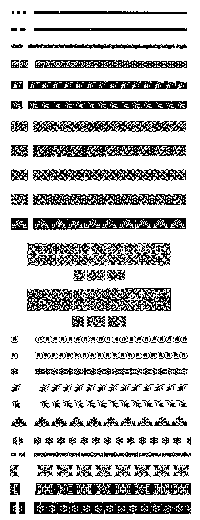
ОТДЕЛ НАБОРНЫХ ШРИФТОВ НИИПолиграфмаша и отечественное шрифтовое дело М. Г. Ровенский |
ОКОНЧАНИЕ. ПРОДОЛЖЕНИЕ В №2. НАЧАЛО В №1 Лаборатория наборных орнаментов и декоративных шрифтов Одновременно с изобретением книгопечатания появились украшения на печатных страницах. Известны образцы использования наборных орнаментов такими крупными деятелями типографского искусства, как Клод Гарамон, Иван Федоров, Эльзевиры, Уильям Моррис и многие другие. В оформлении печатных изданий применяются и абстрактные украшения—простейшие линейки, геометрические фигуры. Словолитни и типографии в царской России имели очень большое количество комплектов наборных орнаментов, зачастую низкого художественного качества. После революции большая часть их была переплавлена в металл. Таким образом были разработаны целые серии орнаментов для ручного набора. В серии «Слава» (худ. Н.Я.Караванский, А.Н.Коробкова) использованы лавровые и дубовые листья с советской эмблематикой. В серии «РСФСР» (худ. Н.Я.Караванский, А.Н.Коробкова, И.С.Слуцкер) взят исходный мотив—лиственный орнамент, названный «Федоровским», который употреблялся на протяжении столетий в старопечатных книгах. В серии «Белорусская ССР» (худ. А.Г.Платунова, А.Н.Коробкова) введены мотивы белорусской вышивки. В серии «Казахская ССР» (худ. А.Г.Платунова, А.Н.Коробкова, Е.Г.Бельская), в серии «Узбекская ССР» (худ. А.Г.Платунова, И.С.Слуцкер, А.Н.Коробкова), в серии «Киргизская ССР» (худ. И.С.Жихарев, Н.А.Перова), «Таджикская ССР» (худ. А.Г.Платунова), «Туркменская ССР» (худ. А.Г.Платунова), «Карельская АССР» (худ. А.Г.Платунова)—во всех перечисленных сериях использовались мотивы соответствующей народной орнаментики. Каждый наборный орнамент, основанный на элементах народного искусства отдельных национальных республик, обогащает художественное оформление издательской продукции, но его применение требует большого внимания и такта. К сожалению, эта большая работа ОНШ, потребовавшая много творческих усилий и материальных затрат, не была полностью использована и внедрена в оформительскую практику издательств. Поход в 60-е годы против «украшательства» в архитектуре сказался и на издательской практике: все это было признано «излишеством». Теоретические работы Основная работа Отдела новых шрифтов всегда состояла в решении художественно-конструкторских задач по проектированию рисунков шрифтов для типографского набора, однако вопросы теории шрифта и истории развития типографского дела также требовали внимания и изучения. Вопросы проектирования и анализ художественного качества шрифта. Практическая деятельность по созданию новых рисунков шрифта требует теоретического исследования, познания эволюции шрифтовых форм и закономерностей их развития. Проводились также и параметрические работы, связанные с различными видами и требованиями проектирования и эксплуатации шрифтов. На основе обобщения отечественного опыта по освоению и использованию зарубежных разработок шрифтов Ф.Ш.Тагиров написал работу на тему «Технологический процесс разработки рисунков копируемых шрифтов». В 1946 году в журнале «Полиграфическое производство» была опубликована статья Ф. Ш. Тагирова «Состояние и перспективы развития печатных шрифтов в СССР». Значительное теоретическое исследование провел Ф.Ш.Тагиров в своей статье «Язык, письменность, шрифт», опубликованной в сборнике «Проблемы рукописной и печатной книги» (М., 1976). Рассматривая вопросы взаимосвязи языка, письменности и шрифта, он пришел к выводу, что «...существует закономерная связь письменности с языком, шрифта с письменностью...» Психофизиология восприятия и удобочитаемость шрифтов Изучение законов зрительного восприятия шрифтов позволяет определить их удобочитаемость как основной показатель качества текстового шрифта. При определении удобочитаемости шрифта нужно учитывать не только легкость распознавания графем, но и пластическое решение шрифта, его художественную форму, эстетику восприятия. В 1945 году профессором В.А.Артемовым и Е.Н.Меллер был составлен обзор экспериментальных работ и исследований в области удобочитаемости шрифтов за период 1935–1945 годы. Наряду с этими исследованиями в ОНШ велись работы по определению величины допусков на межбуквенные пробелы, по установлению зависимости удобочитаемости текстового шрифта от формата полосы набора, по определению пределов использования одного базового рисунка для изготовления пуансонов нескольких кегелей и многие другие. Работы по исследованию опыта в вопросах искусства шрифта и при проектировании типографских шрифтов В 1950–1957 годах под руководством Ф.Ш.Тагирова в отделе была проведена работа по обобщению опыта ведущих мастеров книжного оформления в области искусства шрифта и исследования по вопросам проектирования типографских шрифтов, разрабатываемых художниками отдела. Г.А.Банникова в своем отчете «Процесс проектирования Банниковской гарнитуры» поделилась опытом критического использования исторического наследия при создании своей гарнитуры и прослеживает поиски основного различия между типами шрифтов, рассматривая вопросы классификации. Н.Н.Кудряшев в своем труде «Опыт проектирования текстового шрифта для набора газет» рассказал о первом опыте по разработке отечественного газетного шрифта и сформулировал основные требования, которым должны отвечать газетные шрифты. М.Г.Ровенский в своем исследовании «Шрифт в книжном оформлении Д.А.Бажанова» описал мастерство графических работ Д.А.Бажанова в книжном оформлении, его индивидуальную манеру рисунка шрифта—«Бажановский почерк» и возможность использования рисунка его шрифта для разработки типографской гарнитуры. Выпуск информационных проспектов В Отделе новых шрифтов по мере разработки новых типографских гарнитур возникла необходимость выпуска информационных материалов для ознакомления типографий и издательств с новыми шрифтами, а также для использования этих шрифтов в издательской практике. Особо выделяются по оформлению проспекты, сверстанные по макетам самих авторов—создателей типографского шрифта. Информационный проспект к гарнитуре Акцидентная Телингатера решен по макету С.Б.Телингатера. Признанный мастер искусства книги, долгие годы занимающийся графикой типографского шрифта, показал различные возможности применения своего шрифта в печатной продукции. Известный оформитель книги, мастер каллиграфического шрифта П.М.Кузанян представлен двумя проспектами: к гарнитуре Титульная Кузаняна для строкоотливного, крупнокегельного «СК» и ручного набора, а также к афишно-плакатному шрифту Гранит для ручного набора. Типографский шрифт Пискаревская гарнитура, созданный одним из крупнейших ксилографов, мастером книжной гравюры и оформления книги
Н.И.Пискаревым, показан в различных текстах книжного набора в сочетании с гравюрами и заставками работы автора. Благодаря таким людям можно было выполнять нужную работу по выпуску информационных проспектов. В связи с этим необходимо вспомнить активного участника выполнения всех этих работ по выпуску информационных проспектов А.А.Оносовского. Прошедший воинскую службу матросом, а затем работавший в типографии печатником, он обладал огромной трудоспособностью и любовью к труду. В процессе подготовки к изданию очередного проспекта он доставлял в типографии матрицы типографских гарнитур с набором и сам помогал печатнику готовить печатную форму. Последние годы своей работы в ОНШ он стал мастером-фотографом и добивался блестящих результатов в процессе подготовки оригиналов рисунков шрифта к дальнейшей разработке. Он остался в памяти всех его соратников по работе! |
Наборный орнамент из проспекта–инструкции Советский наборный типографский орнамент, (серия №6), Москва–1959 Наборный орнамент из проспекта–инструкции Советский наборный типографский орнамент, (серия «БССР»), Москва–1961 Лицевая сторона проспекта Новая журнальная гарнитура, Москва–1973 Обратная сторона проспекта Новая журнальная гарнитура, Москва–1973 Лицевая сторона проспекта Гарнитура «НЕВА», Москва–1973 Обратная сторона проспекта Гарнитура «НЕВА», Москва–1973 Лицевая сторона проспекта Гарнитура акцидентная ТЕЛИНГАТЕРА, Москва–1971 Лицевая сторона проспекта Титульная гарнитура «ЛИДИЯ», Москва–1971 Обратная сторона проспекта Титульная гарнитура «ЛИДИЯ», Москва–1969 Лицевая сторона проспекта Афишно–плакатный шрифт «ГРАНИТ», Москва–1966 Обратная сторона проспекта Афишно–плакатный шрифт «ГРАНИТ», Москва–1966 Лицевая сторона проспекта Гарнитура «НАСХИ КНИЖНЫЙ», Москва–1971 Обратная сторона проспекта Гарнитура «НАСХИ КНИЖНЫЙ», Москва–1971 |
Персоналии Теперь , рассматривая деятельность Отдела наборных шрифтов за весь обозримый более чем пятидесятилетний период (1938–1993), нужно признать, что сложившийся коллектив работников отдела сохранил традиции русского типографского шрифта и старался использовать в своей работе мировой опыт развития типографского искусства. |
Ф.Ш.Тагиров, основавший и многие годы возглавлявший отдел, прошел школу Фаворского в двадцатые годы во ВХУТЕМАСе. Обладая обширными знаниями и широким кругозором, он разрабатывал большой круг вопросов по проектированию новых типографских шрифтов и технологии их производства на всех этапах в процессе освоения. Тагирову принадлежит приоритет в создании первых в стране шрифтов особых графических форм, в частности, арабских, индийских и корейских. Он оставил ряд исследовательских работ по вопросам теории шрифта и истории развития типографского дела. Тагиров пользовался большим авторитетом среди художников, типографских и издательских работников. Недаром многие художники-графики называли ОНШ «институт Тагирова». В начале 60-х годов ему ампутировали ногу, но он продолжал работать до 1978 года. |
Н.Н.Кудряшев—первый художник отдела, взявшийся за разработку первого отечественного газетного шрифта. Он создал по разработанной им совместно с З.А.Масленниковой методике самое большое количество типографских гарнитур для различных типов изданий. Среди его шрифтов всеми признанная гарнитура Кудряшевская энциклопедическая, разработанная в 5-ти начертаниях в огромном ассортименте знаков (русских, латинских, греческих, математических, нотных, астрономических, лингвистических, готических, кириллицы, глаголицы и многих других). Ее применение в третьем издании 30-томной Большой Советской Энциклопедии принесло издательству экономию в 4 с лишним миллиона рублей. А гарнитура Словарная Кудряшева, использованная издательством «Русский язык» для набора на 124-х языках народов мира, потребовала разработки тысяч рисунков шрифтовых знаков. Кудряшев отличался необычайным профессионализмом в работе и доскональным знанием наборной техники. Он был одним из немногих проектировщиков наборного шрифта, разрабатывавшим в своих гарнитурах капительные знаки. Кудряшев обладал огромной работоспособностью и оставил после себя большое количество невостребованных замыслов и эскизов, которые могут и должны быть использованы. |
Г.А.Банникова прошла основательную школу как художник-график в ленинградской Академии художеств еще в 20-е годы. Профессор В.А.Левицкий, знаток истории искусства шрифта,который вел курс искусства шрифта в Академии художеств, способствовал тому, что Банникова в своих творческих замыслах пыталась раскрыть художественную ценность типографского шрифта. В своей гарнитуре Банниковская, над которой она работала много лет, на основе тщательного изучения первых русских шрифтов петровского времени и европейских шрифтов эпохи Возрождения Банникова создала первый оригинальный рисунок кириллического шрифта антиквенного типа, предназначенный для набора художественной литературы. Банникова теоретически и практически занималась проблемами сравнительной удобочитаемости шрифтов и различимости отдельных знаков, что нашло отражение в ее шрифтах Банниковской, Байконур, Кама. Она оставила также несколько работ по теории и истории шрифта. |
А.В.Щукин, один из старейших художников отдела, обладал опытом художника шрифта и обширными знаниями по эволюции типографских шрифтов всех исторических эпох. Он многое сделал на первом этапе работы шрифтовой лаборатории НИИ Наркомместпрома РСФСР по модернизации старых типографских гарнитур. Щукин хорошо знал систему «монотип» и практику наборного дела и всегда делился своим опытом и знаниями с молодыми художниками. Он принимал участие в важнейших разработках отдела, таких, как гарнитуры Литературная, Журнальная рубленая (как руководитель темы), Обыкновенная новая, Лазурского, создал оригинальный рисунок типографского шрифта Ладога, в котором форма знаков имитирует технику ширококонечного пера. Щукин обладал замечательным чувством шрифтовой формы, оригиналы его шрифтов долго еще показывали молодым специалистам как пример того, как надо работать. Кроме того, он был прирожденным педагогом, и, по отзывам многих художников следующего поколения, именно Щукин познакомил их с секретами искусства проектирования типографских шрифтов. |